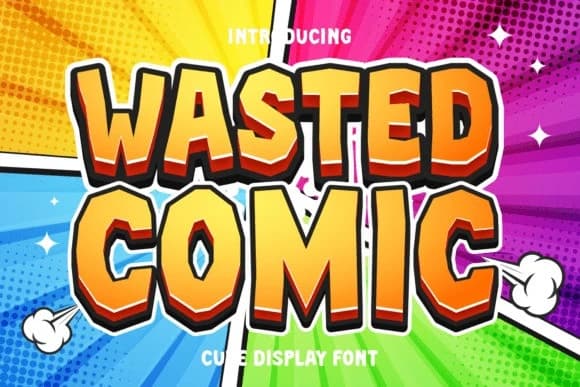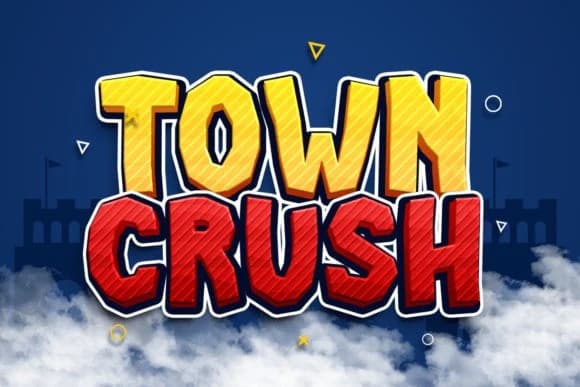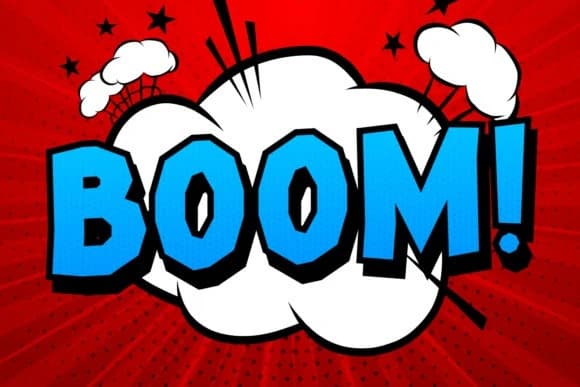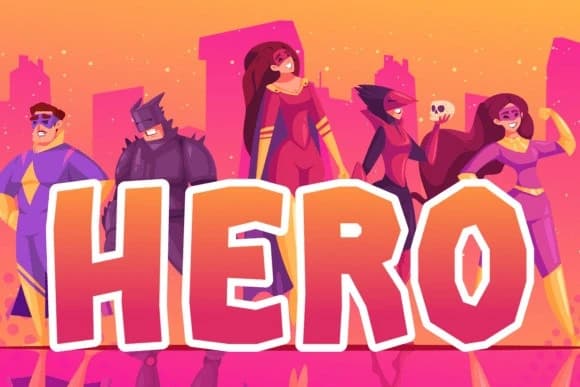
Wasted Comic Font
Wasted Comic Font, çeşitli font stillerinin büyüleyici bir karışımı olan ve zevkli bir görsel deneyim sunan bir yazı tipidir. Bu çok yönlü tipografi şaheseri, çocuk fontlarının eğlencesini, çizgi roman ve süper kahraman fontlarının eğlencesini, güzel ve popüler fontların zarafetiyle bir araya getiri
Wasted Comic Font, çeşitli yazı tipi stillerinin çekici bir karışımıdır ve keyifli bir görsel deneyim sunar. Bu çok yönlü tipografi harikası, çocuk yazı tipi stillerinin eğlencesini, çizgi roman ve süper kahraman yazı tiplerini, güzel ve popüler yazı tiplerinin zarafetiyle birleştirir.